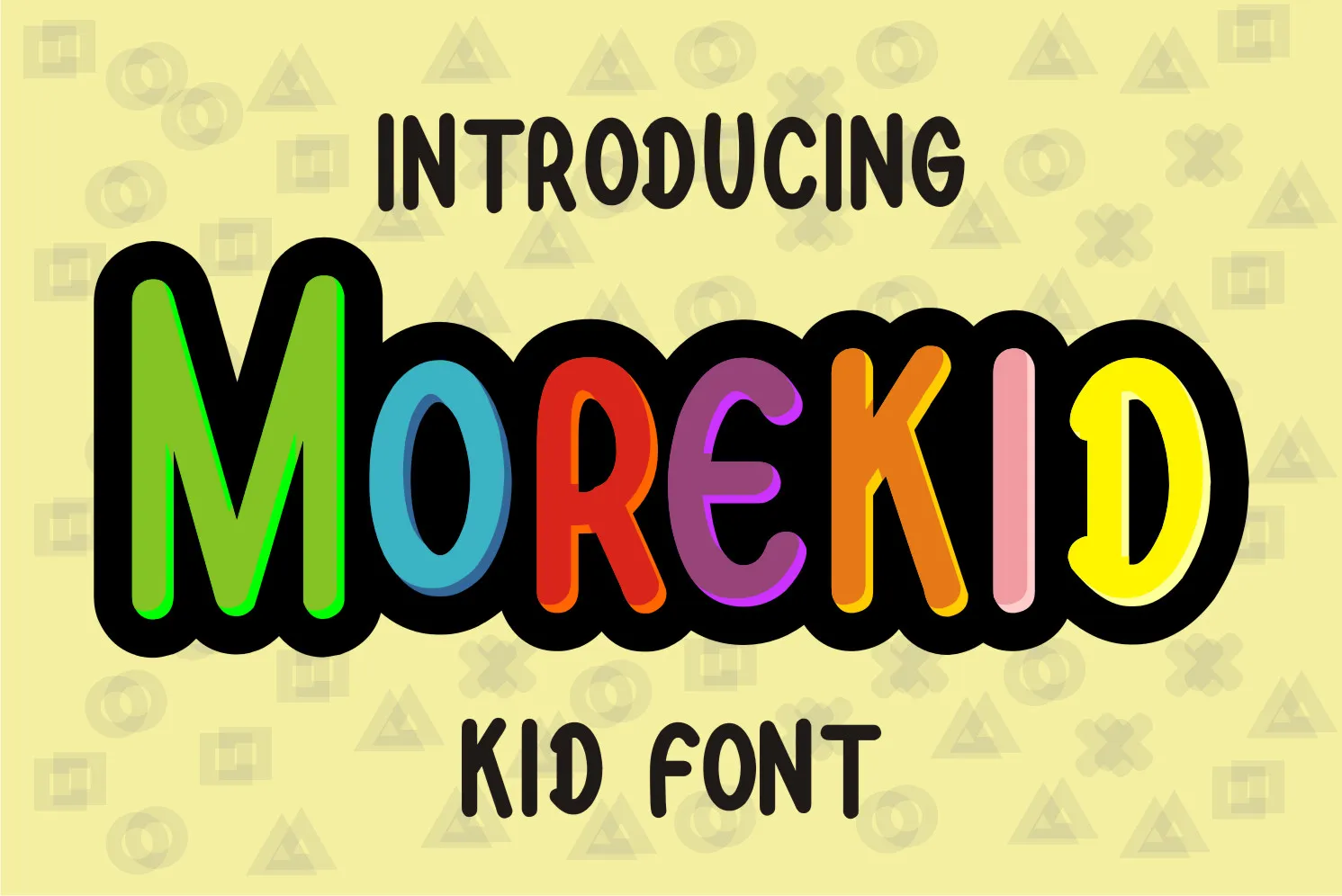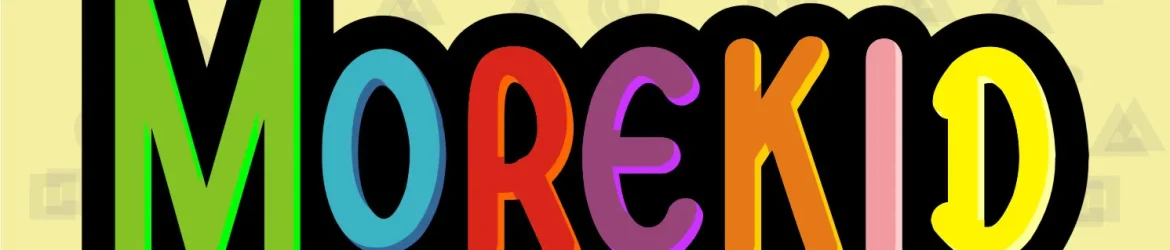
Morekid Font – Download Grátis
A Morekid Font é uma elegante seleção para designers digitais buscam um toque relaxado em seus trabalhos. Ela é projetada para quem valoriza simplicidade e clareza, oferecendo uma maneira criativa de introduzir um ar descontraído e informal em qualquer projeto. Suas linhas leves e limpas se adaptam perfeitamente a diversas aplicações de design gráfico, desde logotipos até fontes para textos longos e complexos. Com seu estilo informal e seu tom relaxante, essa fonte é uma escolha óbvia para qualquer projeto que deseje um toque descontraído. Suas linhas delicadas garantem que a Morekid se destaque de forma moderna e clara na página ou em qualquer outro suporte visual. É uma opção perfeita para quem busca adicionar um touch único sem comprometer o equilíbrio visual da sua criação. Essa fonte, criada pelo designer letterfiastudio, é adequada para designers que buscam um recurso de fontes de alta qualidade e diversidade. Compostas pensadas em detalhes, as Morekid Fonts são uma maneira perfeita de personalizar seus designs digitais, tornando a experiência do cliente única e atraente.